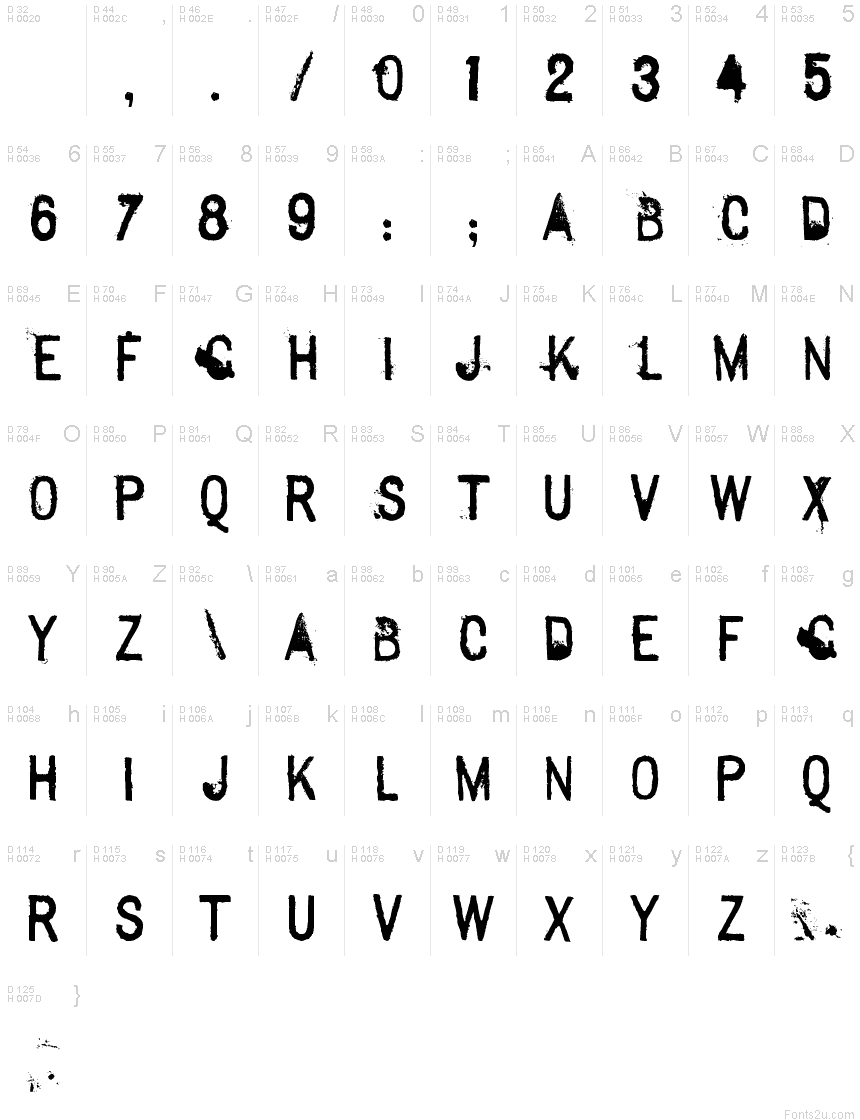
Sexton Sans od Polenimschaufenster fonts je bezplatné erodované titulkové písmo s drsným nábojem punkových letáků. Písmena vypadají jako odřená, oštípaná a lehce nestabilní, s tupými tvary a potrhanými okraji, díky čemuž působí celé písmo spíše jako koláž než čistá kresba.
Tato drsná nálada se hodí na plakáty, obaly desek, ziny, titulní karty a klubový branding, kde krátká slova unesou texturu bez nutnosti dalších ozdob. Jako bezplatný font se skvěle hodí i na obálky, grafiku akcí a výrazné nadpisy, které chtějí odrbaný, ručně vyráběný vzhled přímo z ulice.